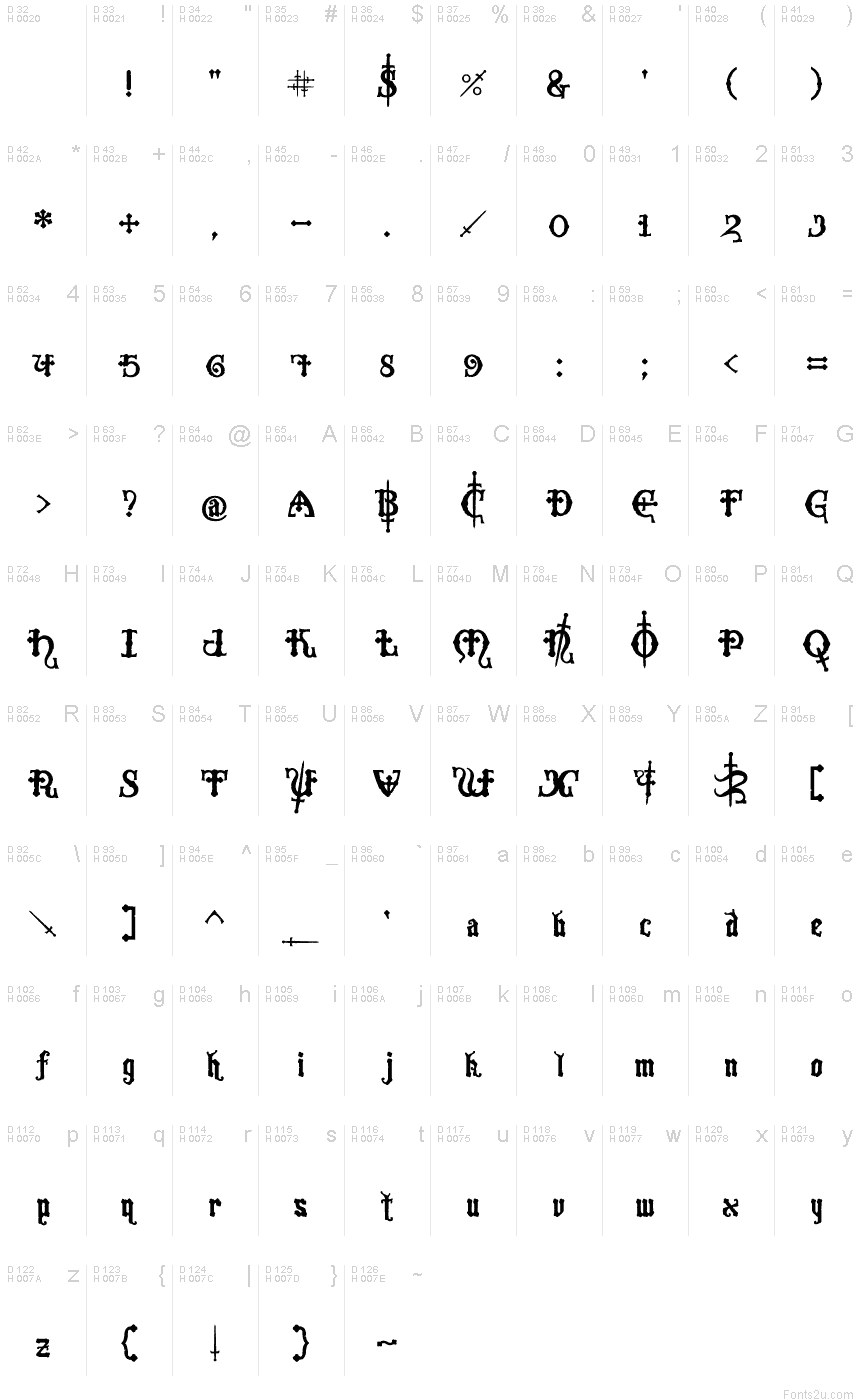
Crusades od Fontsmith je bezplatné gotické středověké písmo, které vypadá, jako by bylo otisknuto do pergamenu inkoustovým razítkem. Písmena působí drsně a ceremoniálně, s výrazným křížovým zdobením, které mění počáteční znak v malý emblém. Díky svému těsnému, hranatému rytmu dodává i krátkým slovům slavnostní, heraldický nádech.
Nastavte Crusades o něco větší, aby vynikly jeho drsné detaily, a pro doprovodný text ho zkombinujte s klidným, moderním bezpatkovým písmem – tento font zdarma nepotřebuje nic víc, aby působil epicky.